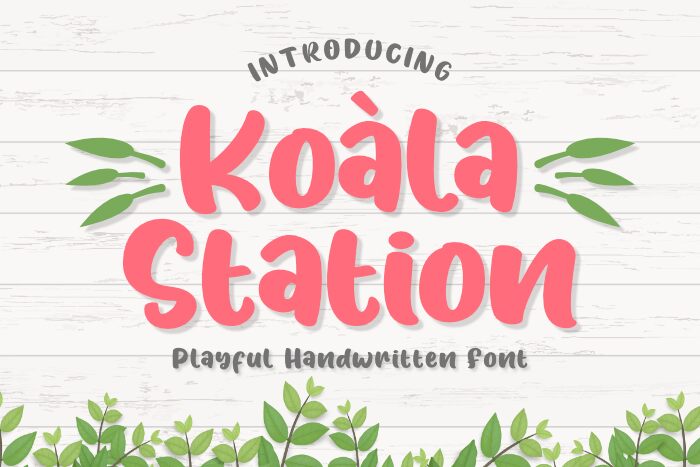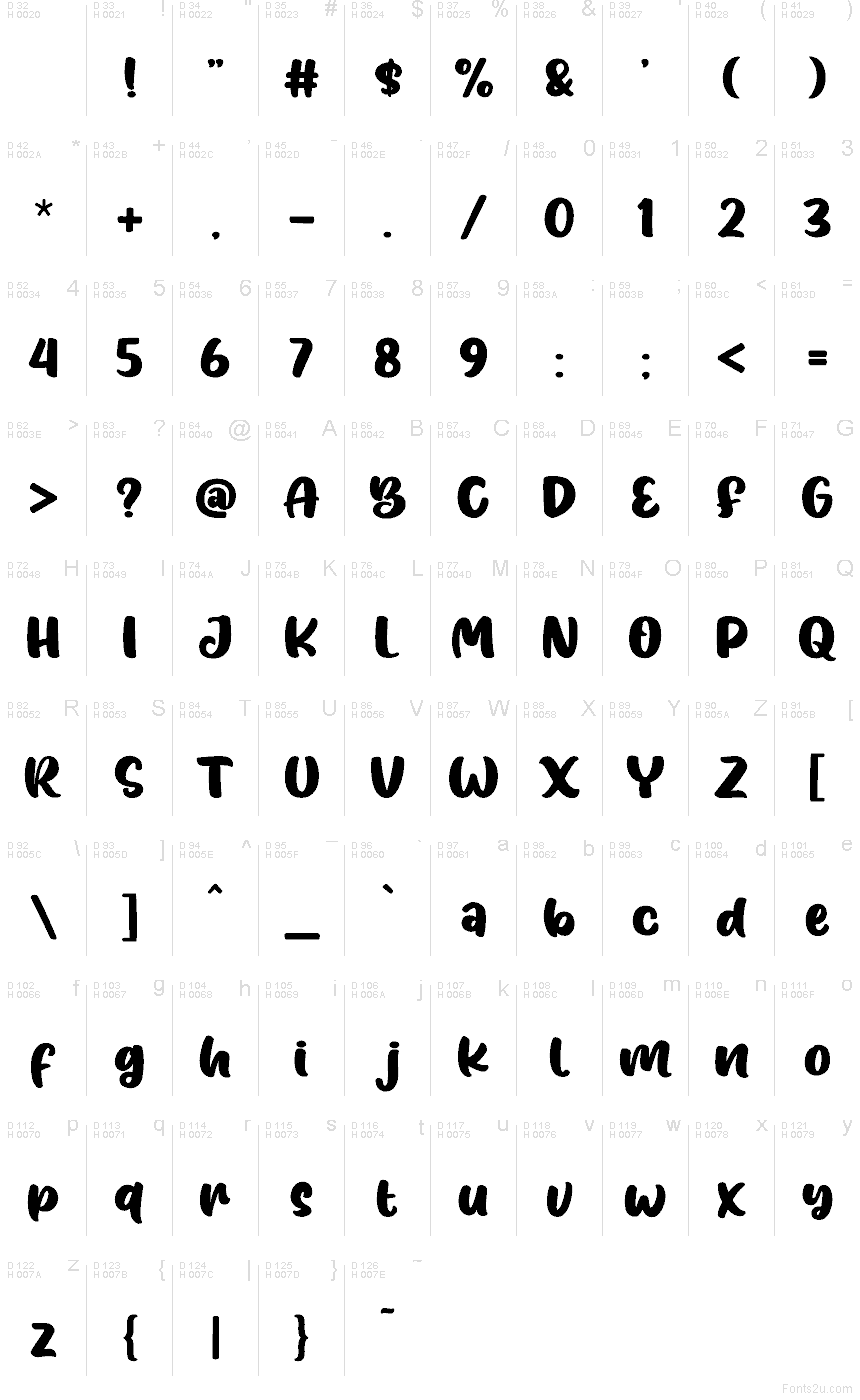
Koala Station par Madatype Studio est une police d'affichage de type cartoon gratuite, dotée de lettres rebondies et irrégulières ainsi que de variations dynamiques de l'épaisseur des traits. De douces courbes, des jonctions pincées et des formes inclinées évoquent les enseignes de magasins peintes à la main.
Sa silhouette enjouée convient à l'édition jeunesse et aux emballages de jouets, tout en s'adaptant à l'identité visuelle de cafés et aux étiquettes de snacks. Ces formes informelles s'adressent aux jeunes publics et aux entreprises familiales recherchant un lettrage qui donne l'impression d'avoir été dessiné plutôt que composé.